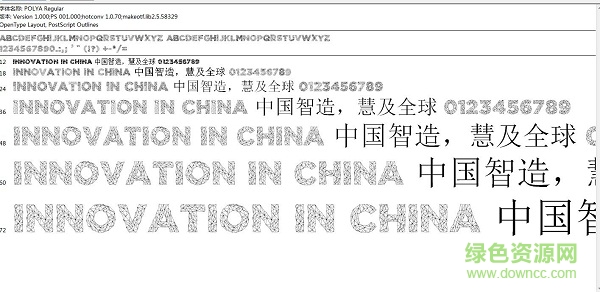
polya 支持中文字體嗎?polya regular是一款獨(dú)特的英文廣告字體,暫不支持中文輸入,字體呈灰白色,可以用在網(wǎng)店裝修、平面設(shè)計(jì)、創(chuàng)意設(shè)計(jì)等方面,有需要者歡迎免費(fèi)下載!
Polya字體來(lái)源于3D計(jì)算機(jī)建模,他是一種具有粗字體和輕量級(jí)別外觀的字體。